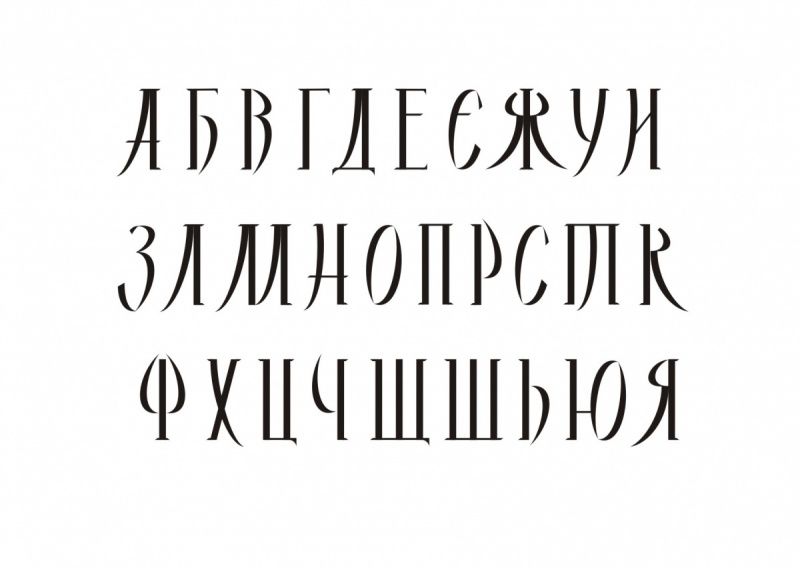
1. Шрифты для транслитерации санскрита
Восточные шрифты связаны с проблемами. Не подозревая о них, даже имея правильный текст на входе, на выходе получите крякозабры, кашу или пустоту.
Провереных шрифтов для санскрита — считанные единицы. В Индии не подозревают даже о существовании современных шрифтов, да и что и говорить — они и по сей день верстают книги в Adobe PageMaker, реже Quark а не (отвратительном, но лучшем среди худших) в Adobe InDesign. Действительно мастера верстают в LaTeX, но только те, кто имеют математический бэкграунд.
«Кришнаитский» шрифт для транслитерации на основе кириллицы
- Times New Roman Dev (скачать тут)
Кириллический шрифт, стилизованный «аля деванагари» («под санскрит»). То есть можно издать прабхупадовскую Бхагавадгиту. - ThamesM (скачать тут)
Сделан на основе курсивного Charter как замена более пошлому Times New Roman, однако до печати так и не дошел, остался невостребованным.
Шрифт-стилизация для кириллицы
- Jaipur — редкая стилизация под деванагари, хотя некоторым навеивает мысли об армянском письме
- DS Izmir — на каждом заборе в России, чересчур часто употребляем и тем самим изрядно надоел.
Архаичный шрифт для транслитерации на основе латиницы («почти-IAST»)
- Times New Indologique
Шрифт страшен. Единственный, но весьма популярный использователь морально устаревшего шрифта — Н.П. Лихушина, откуда он проник и в изданиях Учебника санскрита В.А. Кочергиной 2017 г. и 2018 г, в «Избранных переводах буддийских сутр» и в обеих изд. «Легкого санскрита».
Его нельзя просто убить, ибо сконвертировав в юникод в неправильной последовательности получите испорченный текст, который потребует месяцев правки. Как правильно убить шрифт.
Академичиский шрифт («юникод») для транслитерации на основе латиницы («IAST»)
- Charter Indologique — основной шрифт, им набран основной русский текст «Хрестоматии» Н.
П. Лихушиной и «Учебник санскрита» Кочергиной 2015 г.- Charis SIL — бесплатная разновидность Charter для лингвистов (скачать тут). Содержит лишь базовые знаки (комбинации диакритик, например, знак одновременно краткости и долготы не доступен)
- Clarendon Dev — альтернатива Чартеру, им набраны слова в латинской транслитерации в Хрестоматии» Н.П. Лихушиной и в грамматике Макдонеля 1927 г.
Чартера и Кларендона достаточно для издания современной книги по санскриту на русском языке. Если речь о репринтах дореволюционных книг, тогда следует рассмотреть Old Standard и Helios, подражая старой стилистике.
- Old Standard Indologique — для текста предисловий репринтов до 1917 г., альтернатива Чартеру «под старину», узкий шрифт с засечками. Подобным шрифто печатали филологические издания в XIX в.
- Helios Indologique — рубленый шрифт для заголовков репринтов до 1917 г.
- Titus Cyberbit Basic — предтеча Charis на основе Times, типографически небезупречен, но содержит разные редчайшие комбинации знаков.
Имея Чартер и Кларендон необходимость в нем отпадает (скачать тут)
2. Шрифты для санскрита (деванагари)
Архаичный шрифт деванагари для записи классического санскрита (используют в Индии)
Единственное преимущество у данной группы шрифтов, которые следовало бы искоренить, но сделано это не будет, ибо шрифтовая культура в Индии крайне консервативна и находится в каменном веке, в том, что можно извлечь текст из PDF без потерь (ибо это изначально некий эрзац и для сохранности текста это, оказывается, ровно то, что необходимо). Текст, набранный на современном шрифте деванагари из PDF извлечь невозможно, он записан как каша.
- Kruti Dev —
- AriaDev2, ArialDev, CournDev — на свалку истории. (см.)
- Sanskrit 1.2 —
- Gudakesa 99 — реплика «французского» начертания шрифта деванагари («старый» стиль), статья о нем.
Современный шрифт («юникод») деванагари для записи разного санскрита
- Sanskrit 2003 — распространенный обновленный шрифт на основе рисунка Sanskrit 1.
2; - Siddhanta — тонкий плод фантазии современного каллиграфа, содержит оба начертания (из-за ограничений Windows это не один шрифт, а целое семейство шрифтов, в частности) шрифта деванагари с невероятным количеством лигатур («новейший» стиль). (скачать тут)
Gudakesa, Santipur, Jaini сделаны под старину. При этом Gudakesa до сих пор не сконвертирован в юникод в отличии от Santipur, который с 2014 г. даже дружит с InDesign.
- Santipur OT — реплика «немецкого» начертания шрифта деванагари («новый» стиль). (скачать тут)
- Jaini — стилизация под джайнскую рукопись (2 варианта, см. пример комбинации деванагарского Jaini и Charter в русском тексте ниже на карточке)
Конвертеры деванагари
Если имеете текст в транслитерации, а нужно получить текст на деванагари (или продублировать его).
Если имеете текст на деванагари, а нужно получить текст в транслитерации.
Насчет того, что шрифт становится более пестрым от диакритики… Есть такой аргумент, но мне он не очень нравится, какой-то он глупый. Ну пестрый… Бессмыслица какая-то.
ЮО: Скорее речь не о пестрости, а о живости.